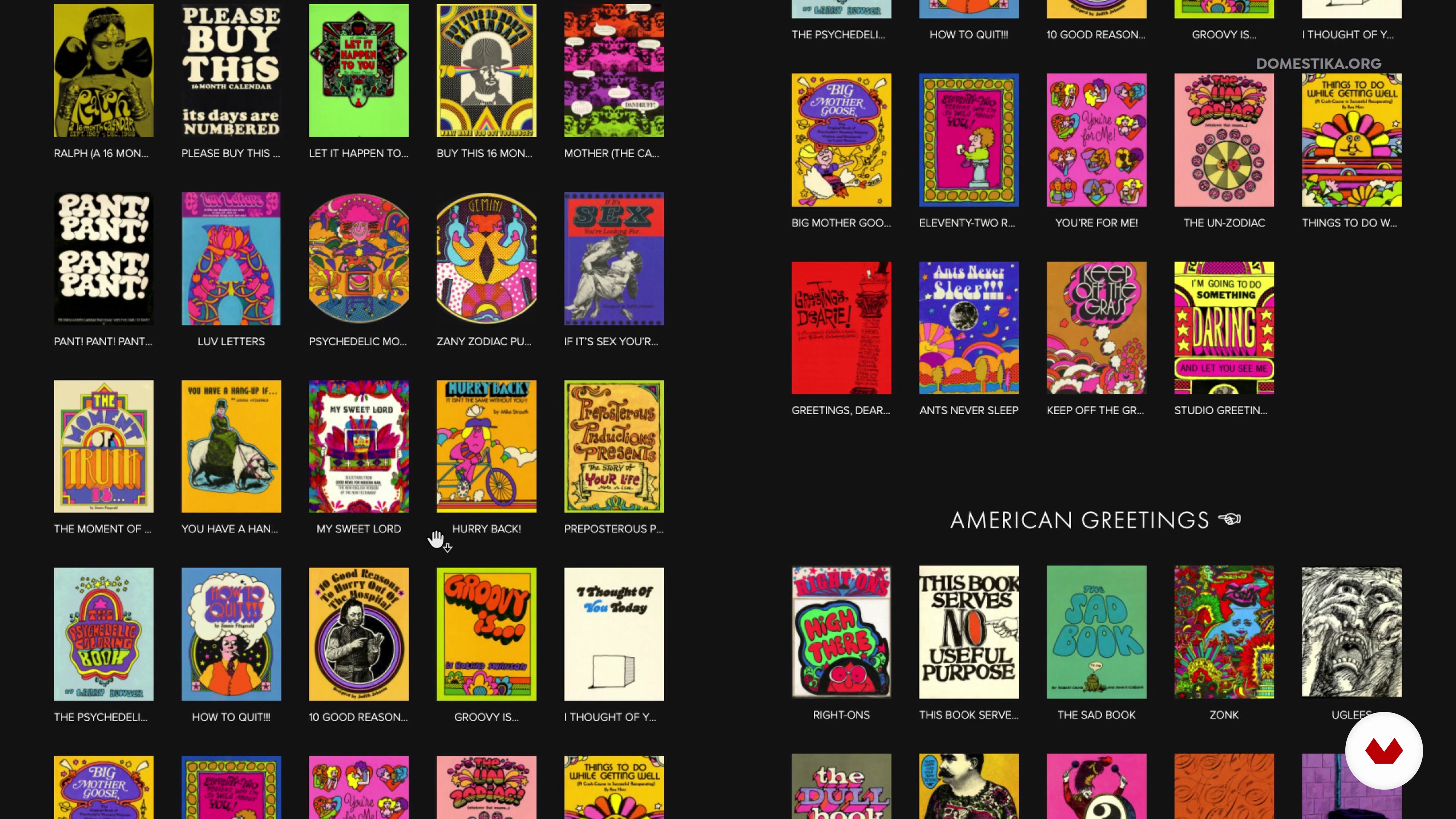
Arquétipos tipográficos
Sobre a videoaula: Arquétipos tipográficos
Visão geral
“Nossas escolhas de fonte provocam reações emocionais e, nesta aula, você conhecerá quais são as associações mais comuns e como podemos acertar o tom de voz visual dos nossos projetos a partir dessas escolhas. ”
Nesta videoaula, Álvaro Franca aborda o tópico: Arquétipos tipográficos,que faz parte do curso online da Domestika: Fundamentos da tipografia de A a Z. Descubra as possibilidades da seleção tipográfica para transmitir e potencializar sua mensagem .
Transcrição parcial do vídeo
“Arquétipos tipográficos Já tem uns 500 anos que a gente imprime com letras pré-fabricadas. Nesse meio tempo, muita gente foi adicionando ingredientes e mudando um pouco as formas de letras. As letras como qualquer manifestação cultural vão absorvendo e refletindo o espírito do seu tempo. Nessa aula, vamos aprender o que estamos dizendo com a nossa seleção tipográfica e como usar a História como um ingrediente nas nossas peças gráficas, vamos lá. ARQUÉTIPOS TIPOGRÁFICOS A gente já sabe que a tipografia tem que transmitir uma mensagem para o leitor. Mas o que não pensamos com frequência é que...”